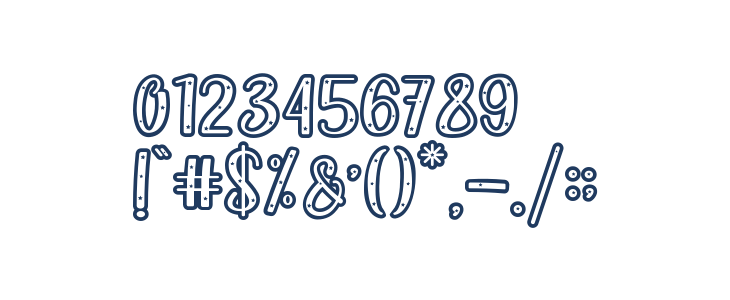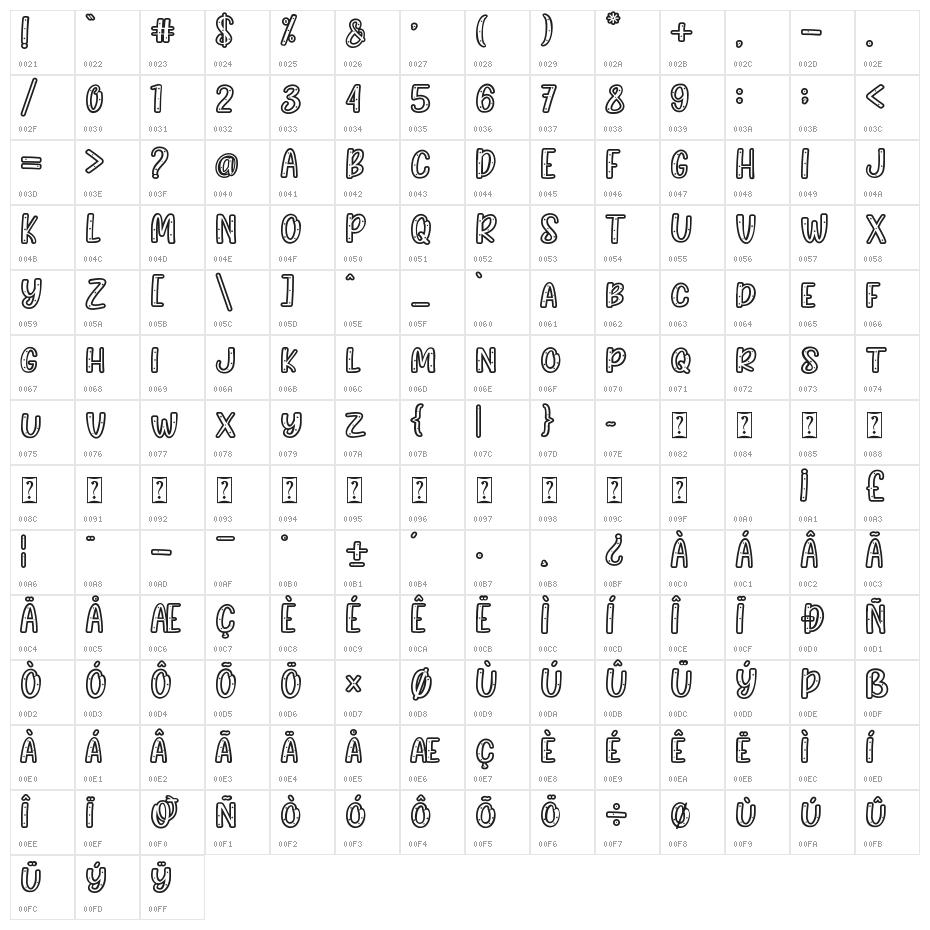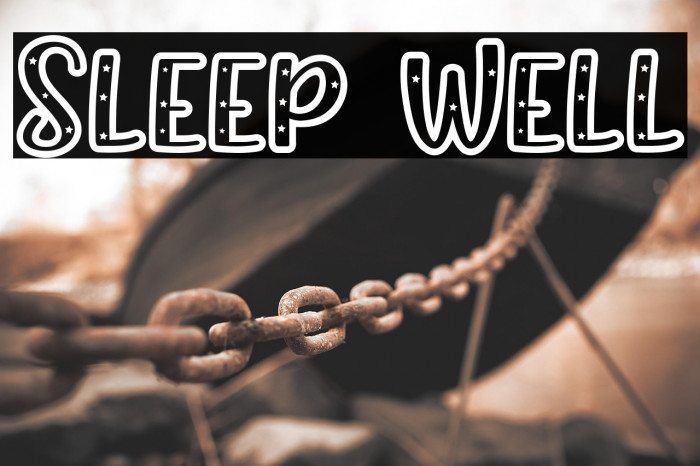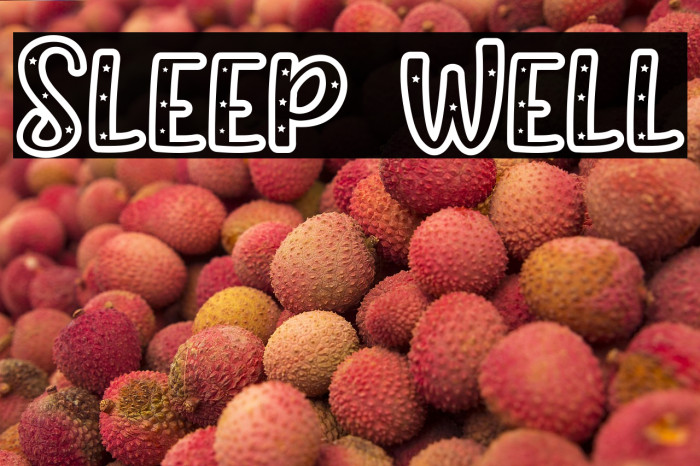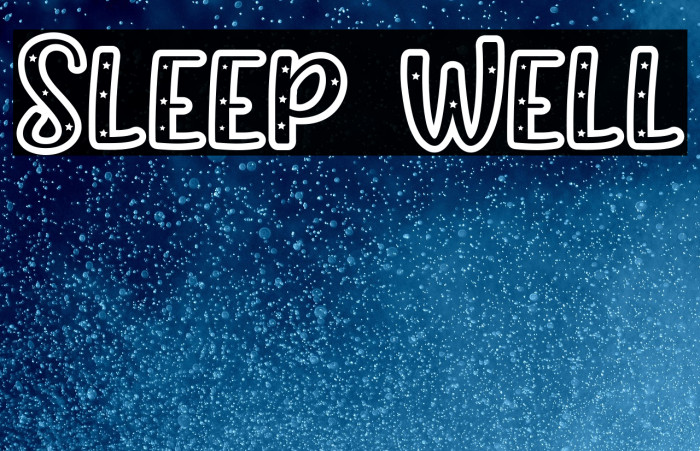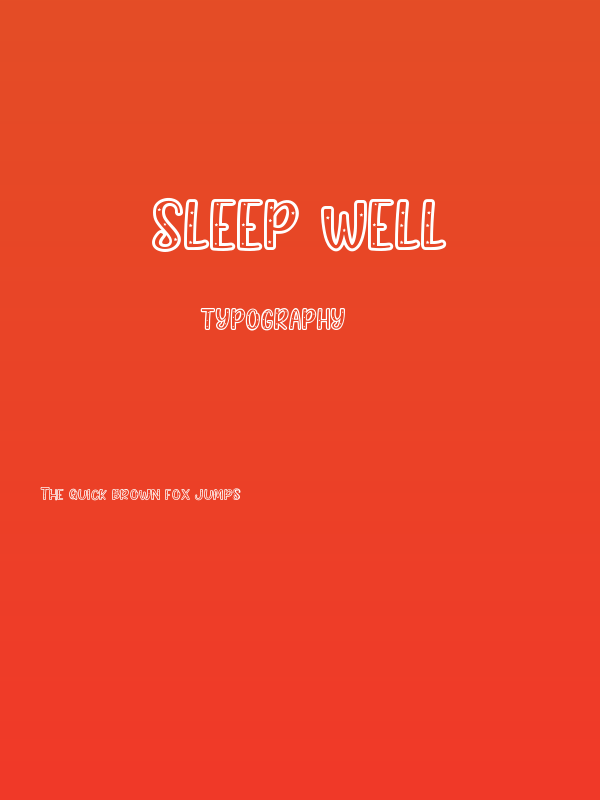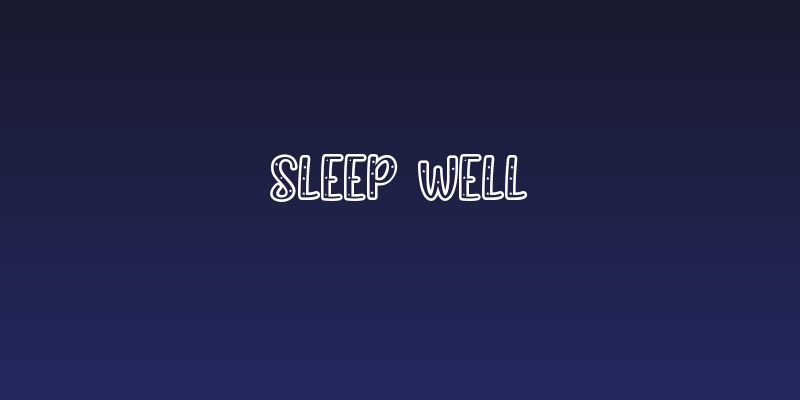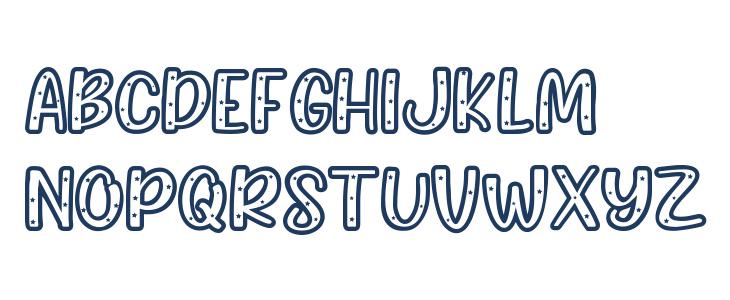
Sleep Well Font
| Progetti proposti | Perfect for children's book covers, party invitations, playful branding, and any project needing a fun, whimsical touch. |